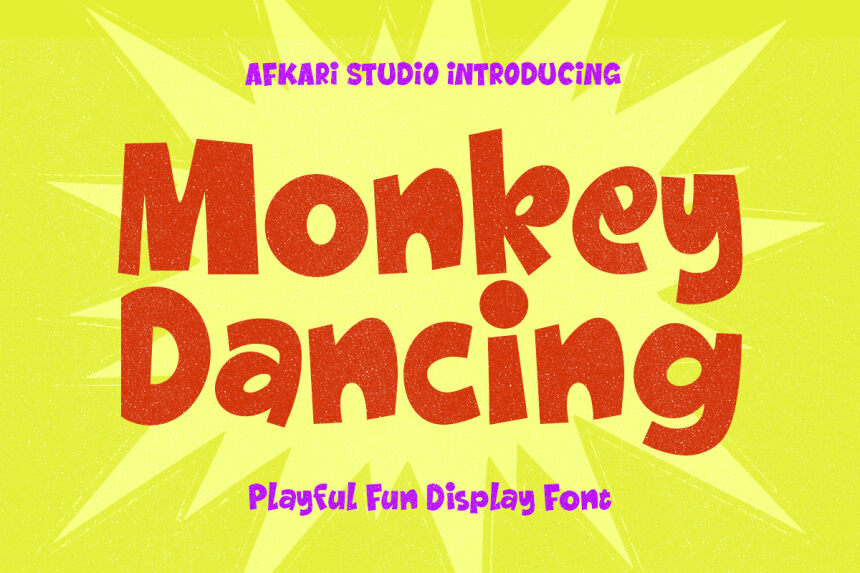
Monkey Dancing de Afkari Studio es una tipografía display gratuita estilo cartoon con un ritmo suelto y saltarín, cargada de un encanto artesanal. Las letras se sienten robustas y juguetonas, con curvas suaves, ángulos ligeramente inclinados y una irregularidad amable que mantiene el dinamismo en el diseño en lugar de buscar la perfección geométrica.
Encaja perfectamente en la identidad visual de productos infantiles, paquetes de snacks, carteles de fiestas, títulos estilo cómic y publicaciones sociales alegres, donde una fuente gratuita puede transmitir el tono incluso antes que cualquier ilustración. Úsala para titulares cortos, portadas o tarjetas de título cuando busques letras que transmitan movimiento, ya que sus formas redondeadas y su actitud desenfadada le dan a cualquier texto un toque divertido y animado.